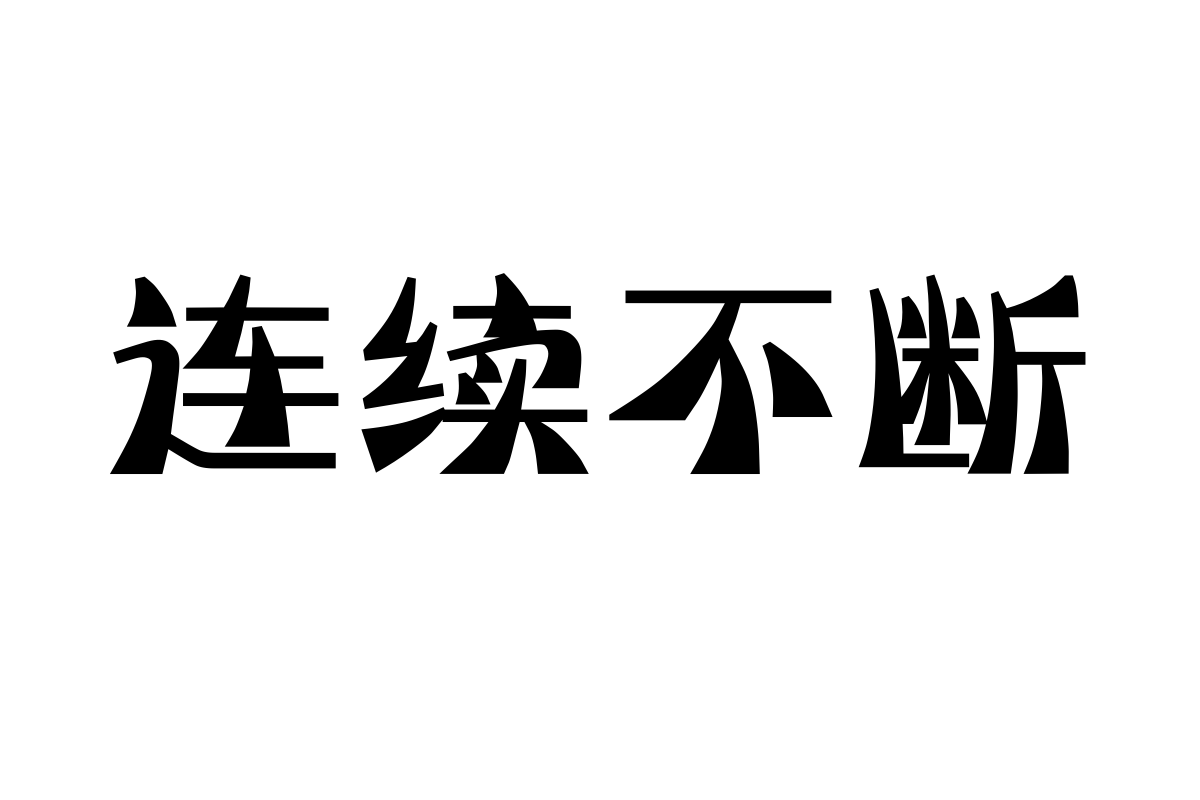
迷你简海韵是一种现代的中文字体,由设计师在2019年设计。这款字体的特点是字形简洁,线条流畅,适合用于各种需要清晰易读的文字排版。它的笔画粗细适中,既有力度又有柔美,给人一种优雅的感觉。
迷你简海韵的字体特点包括:
– 字形简洁,线条流畅
– 笔画粗细适中,既有力度又有柔美
– 适合用于各种需要清晰易读的文字排版
总的来说,迷你简海韵是一款适合现代商业、广告、杂志等多种场合使用的高质量字体。